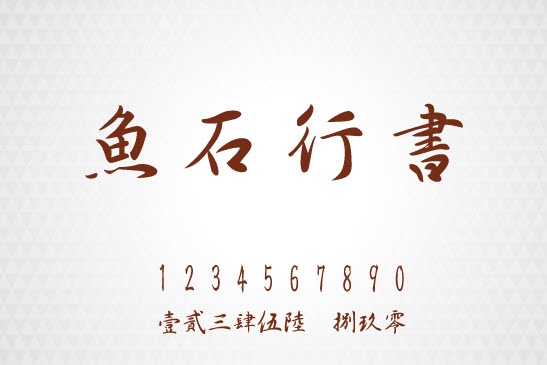
魚(yú)石行書字體是一款非常有個(gè)性的行書字體,筆法鋒利硬朗,非常的剛勁有力,寫出的中文和繁體字,有一種濃厚的古風(fēng)氣息,歡迎喜愛(ài)的朋友到綠色資源網(wǎng)下載使用!
魚(yú)石行書字體是小編一直以來(lái)都蠻喜歡一個(gè)非常好看的書法字體,話說(shuō)小學(xué)時(shí)練毛筆字,初練是可是吃了不少苦頭,不過(guò)后來(lái)還是很行的哦,咳咳,扯遠(yuǎn)了,我們現(xiàn)在推薦這款電腦上使用的字體給大家使用,不過(guò)需要注意魚(yú)石行書只支持繁體中文哦!